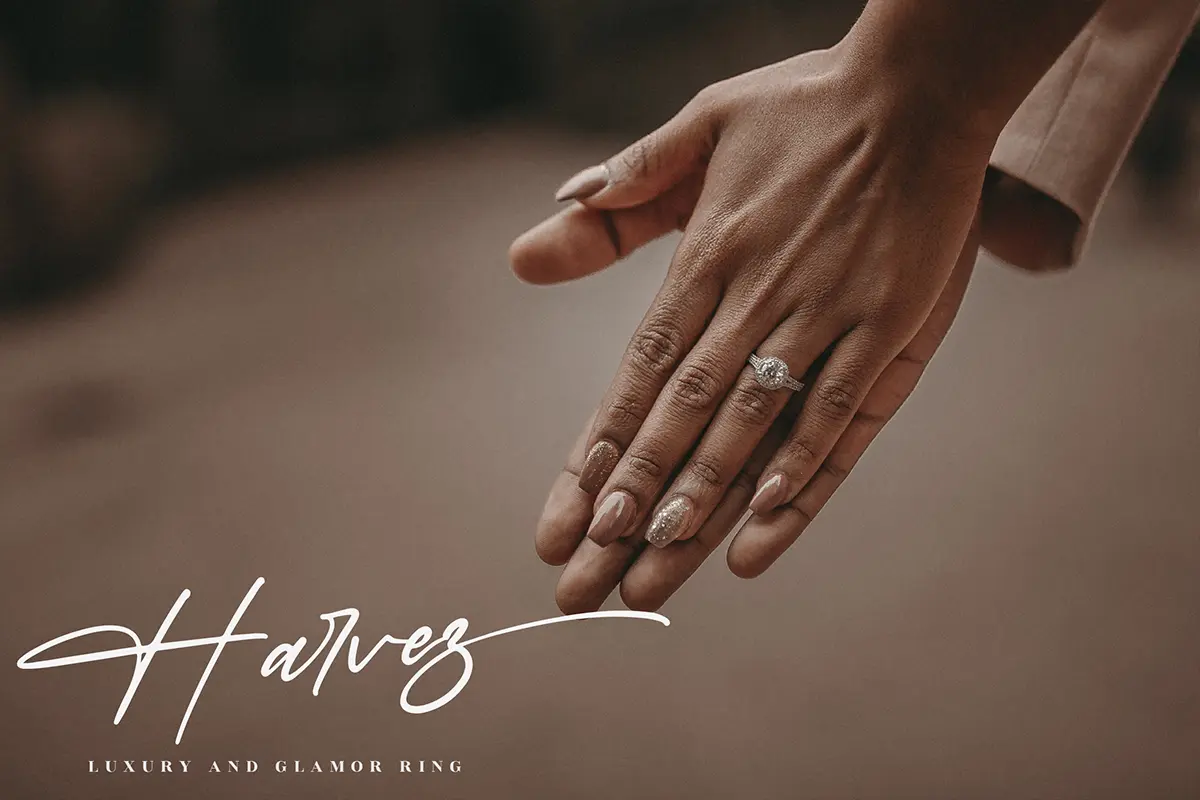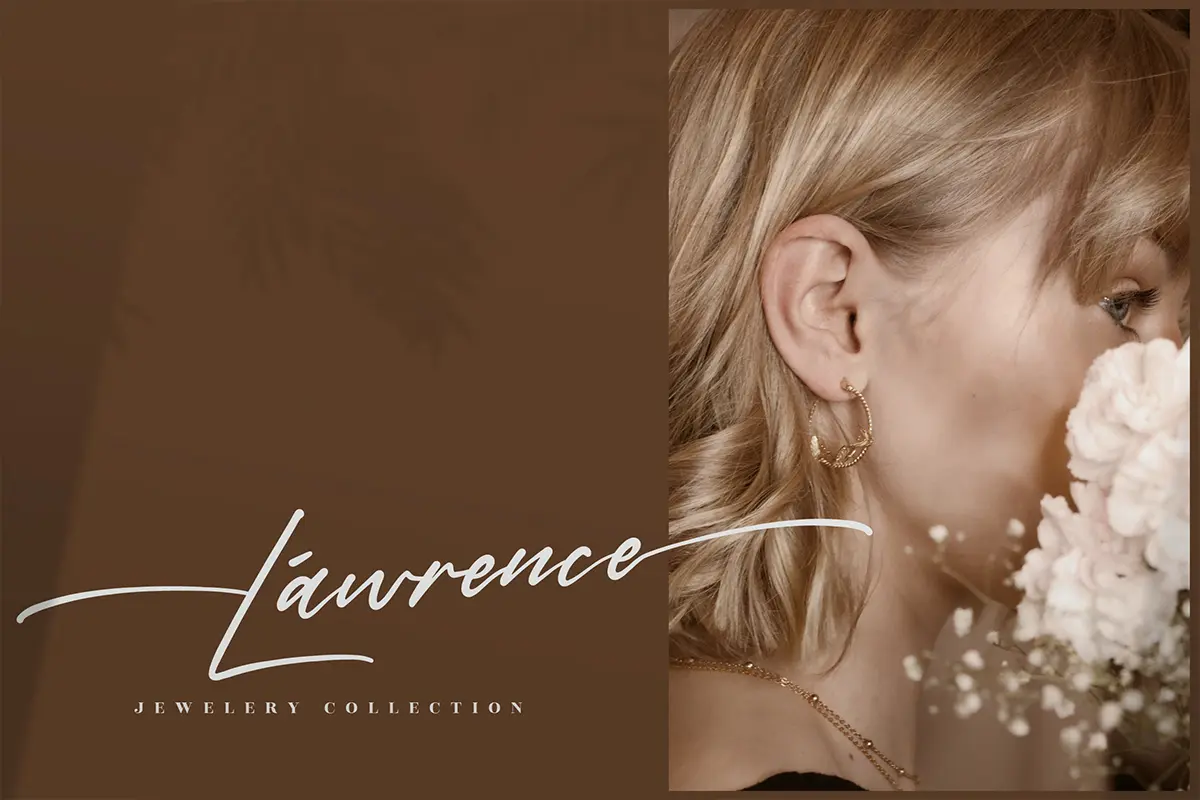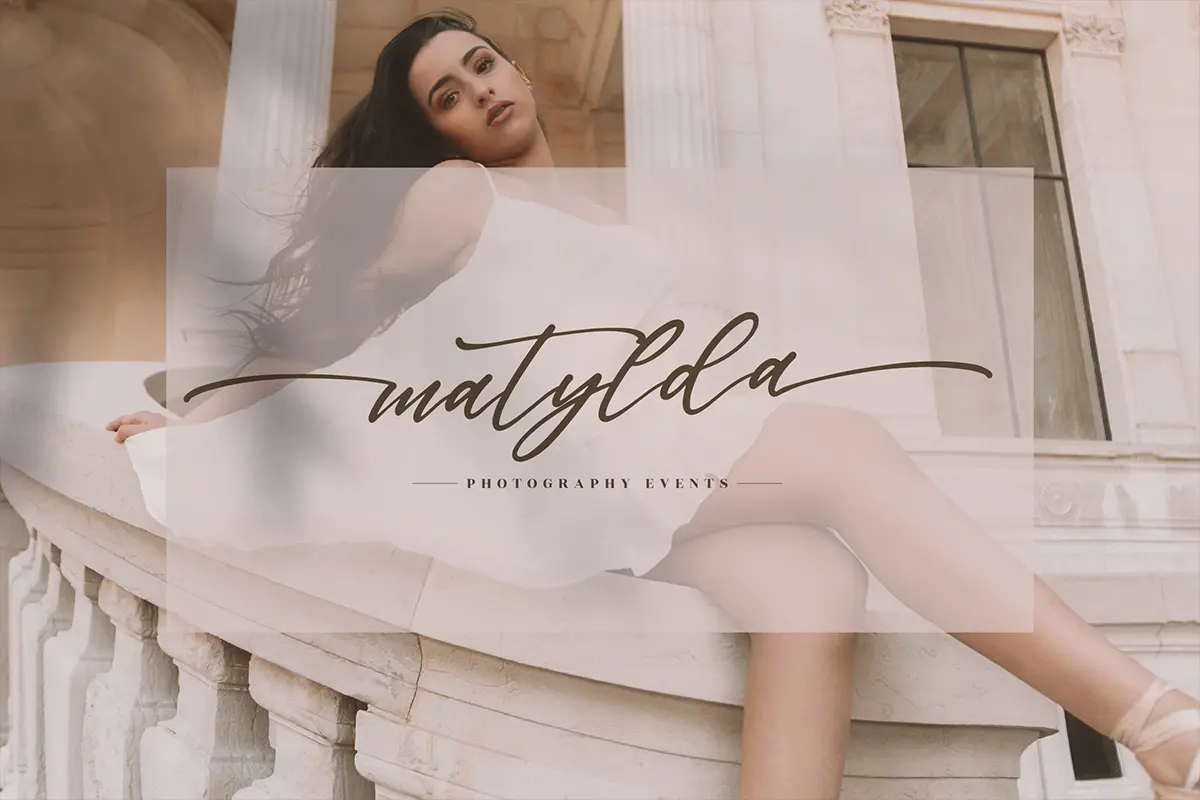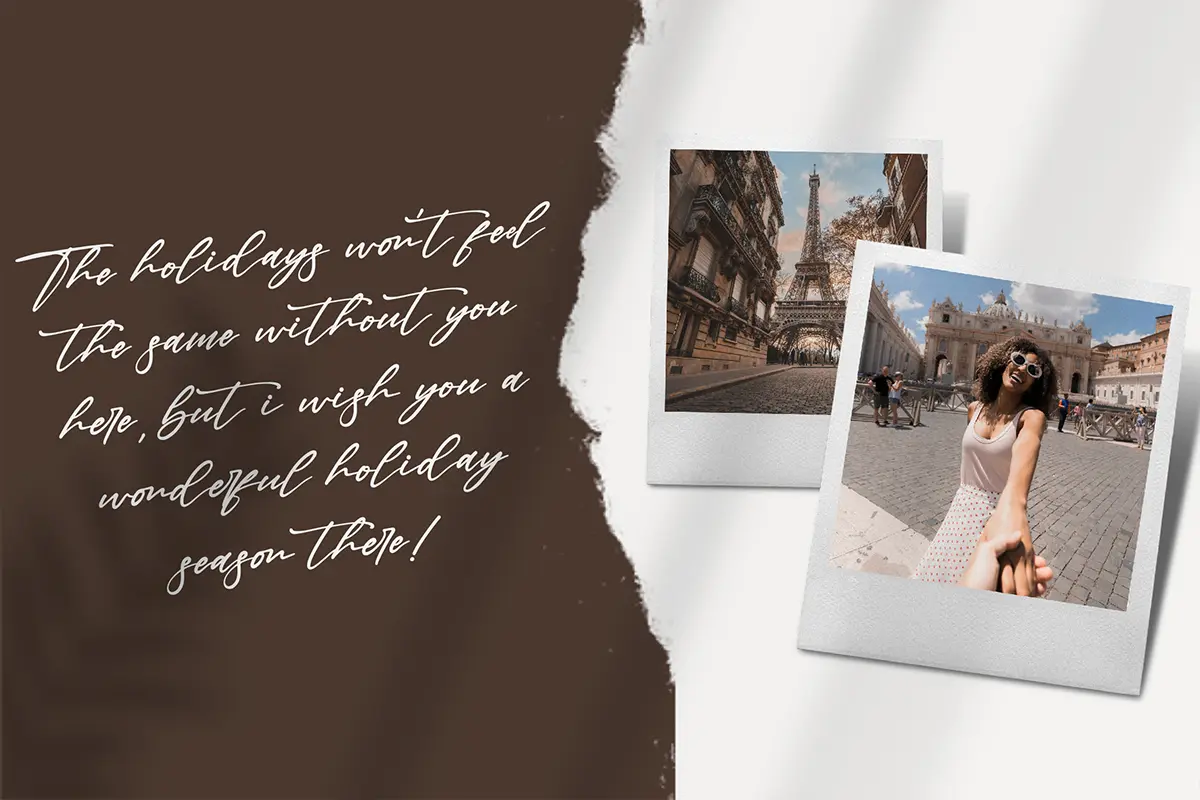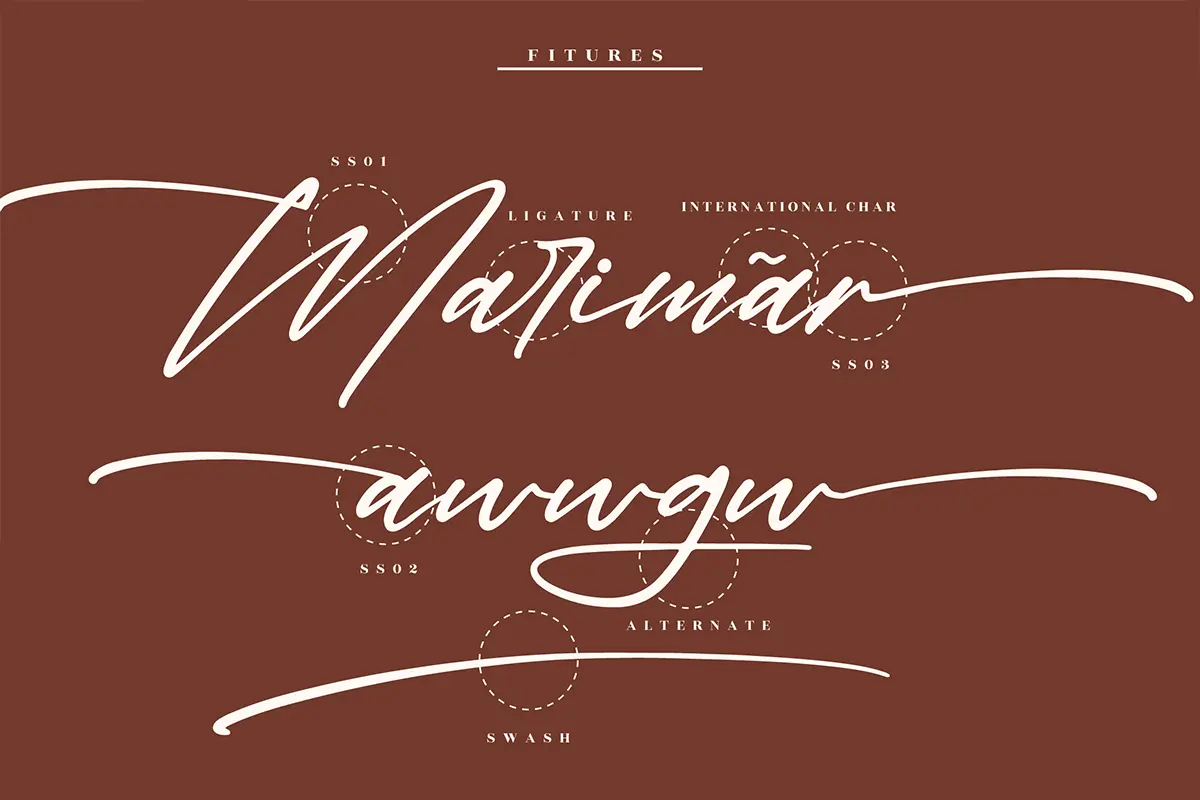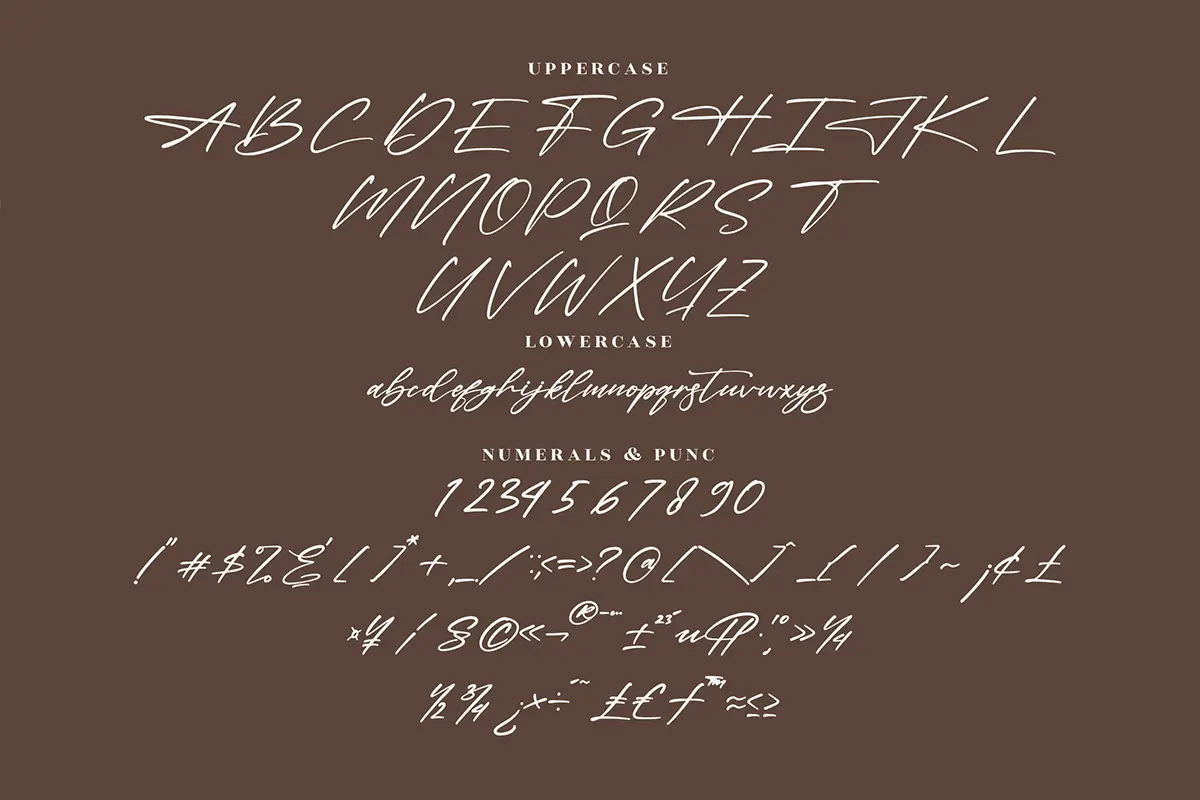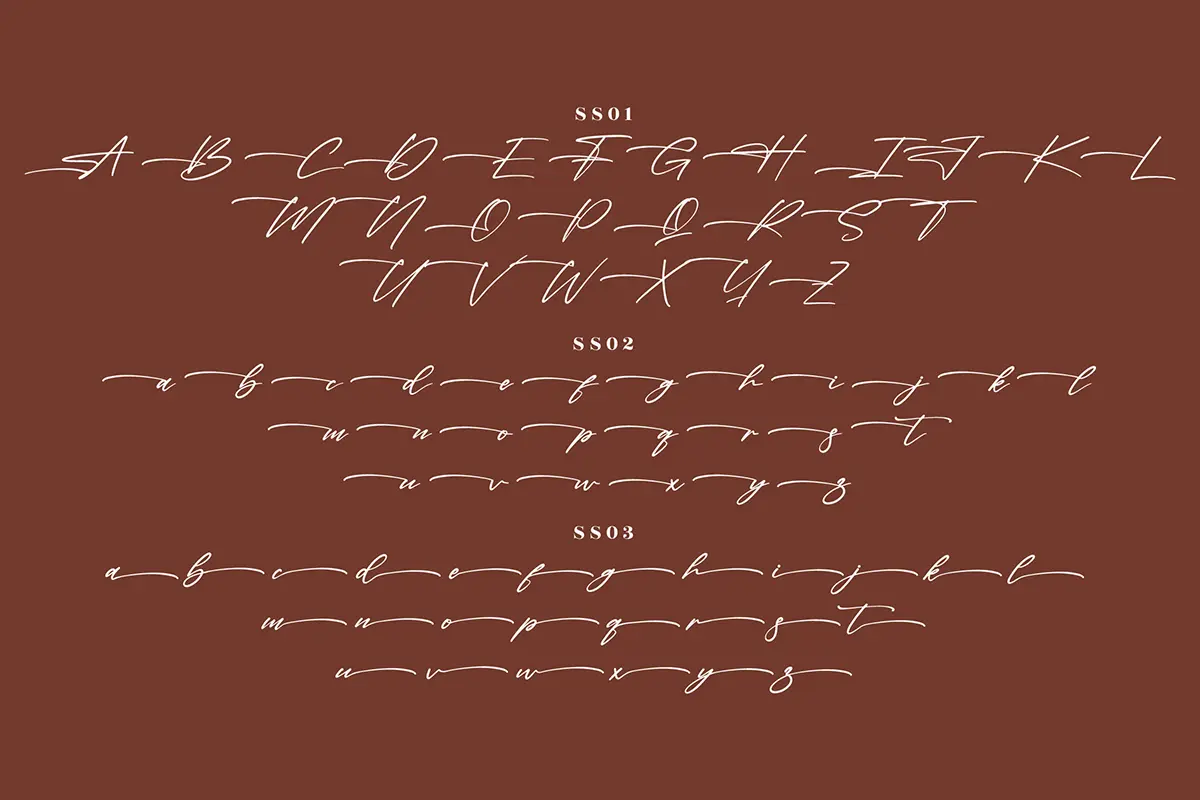
فونت دستنویس سبک امضا
فونت Contage Bright یک فونت اسکریپت ظریف و دوستداشتنی به سبک امضا است که حس ظرافت و کلاسیک بودن را به طراحیهای شما اضافه میکند. این فونت بهطور ویژه برای کسانی ساخته شده که به دنبال جلوهای زیبا و تازه در آثار خود هستند.
⭐ ویژگیهای محصول
- سبک اسکریپت دستنویس ظریف و شیک
- مناسب برای طراحیهای دعوتنامه، کارتهای تبریک، نقلقولها و لوگوها
- انتخابی عالی برای پروژههای برندینگ و کارتهای ویزیت
- جلوهای هنری و کلاسیک برای هر نوع طراحی
🎯 موارد استفاده
- طراحی دعوتنامههای رسمی و عروسی
- ساخت کارتهای تبریک و تشکر
- استفاده در لوگو و برندینگ شخصی یا تجاری
- افزودن به پورتفولیو طراحان گرافیک
- مناسب برای پروژههای چاپی و دیجیتال